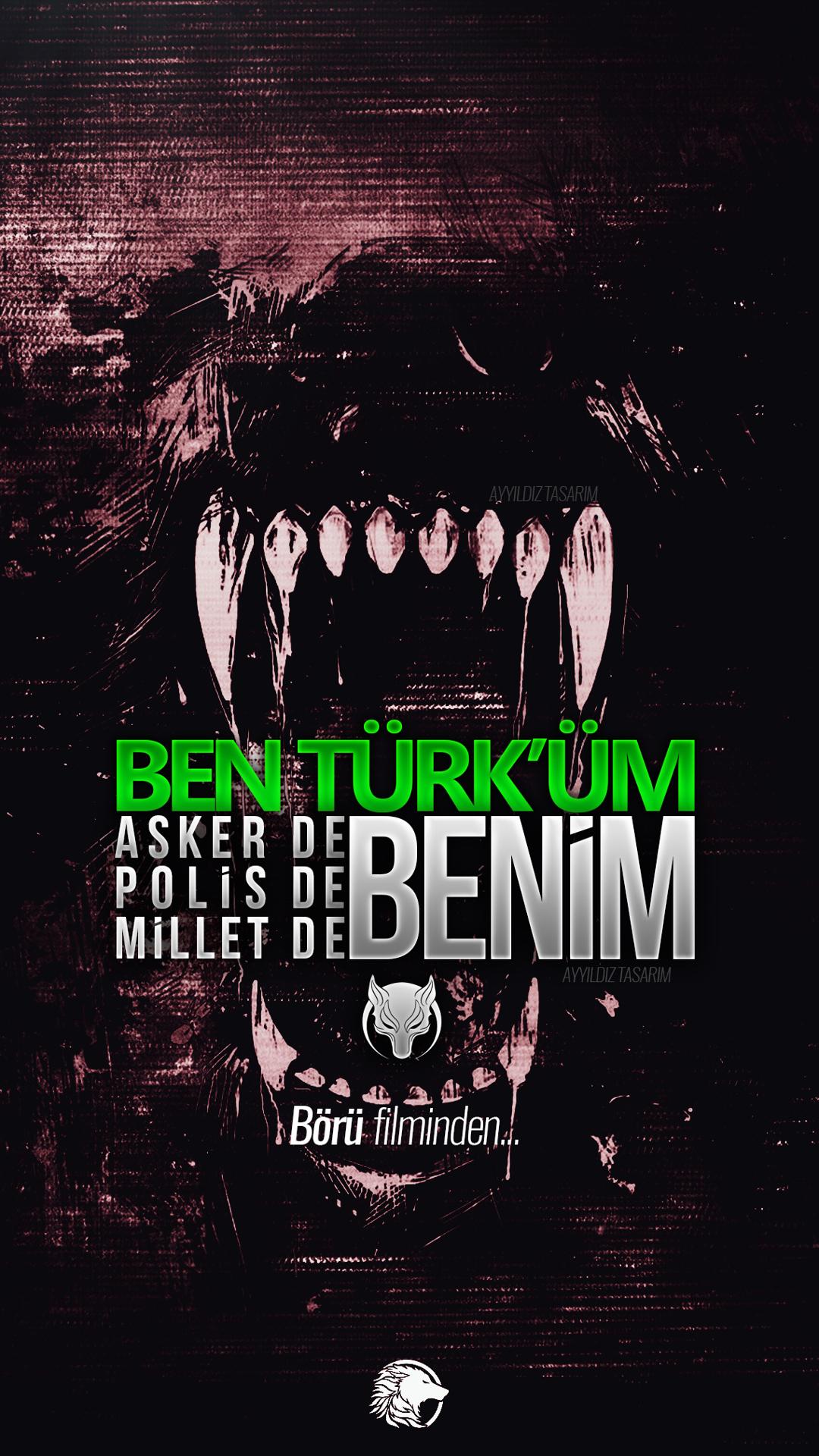
Bu Font'u Bulabilirmisiniz?
Ben Türk'üm yazılı olan fontu bulabilirmisiniz ya? O kadar uğraştım bulamiyorum
WhatTheFont denediniz mi hocam
Lemon Milk olabilir
whatthefont sitesinden denediniz mi hocam? Ufak bi işlem görmüş gibi, harfler yakınlaştırılmış.
PMN Caecilia Sans Pro Head Heavy
Benzer bir font kullanmak isterseniz 'Bebas Neue' önerebilirim.
Font Bebas Neue, üzerinde oynama yapılmış "İ" harflerinde.